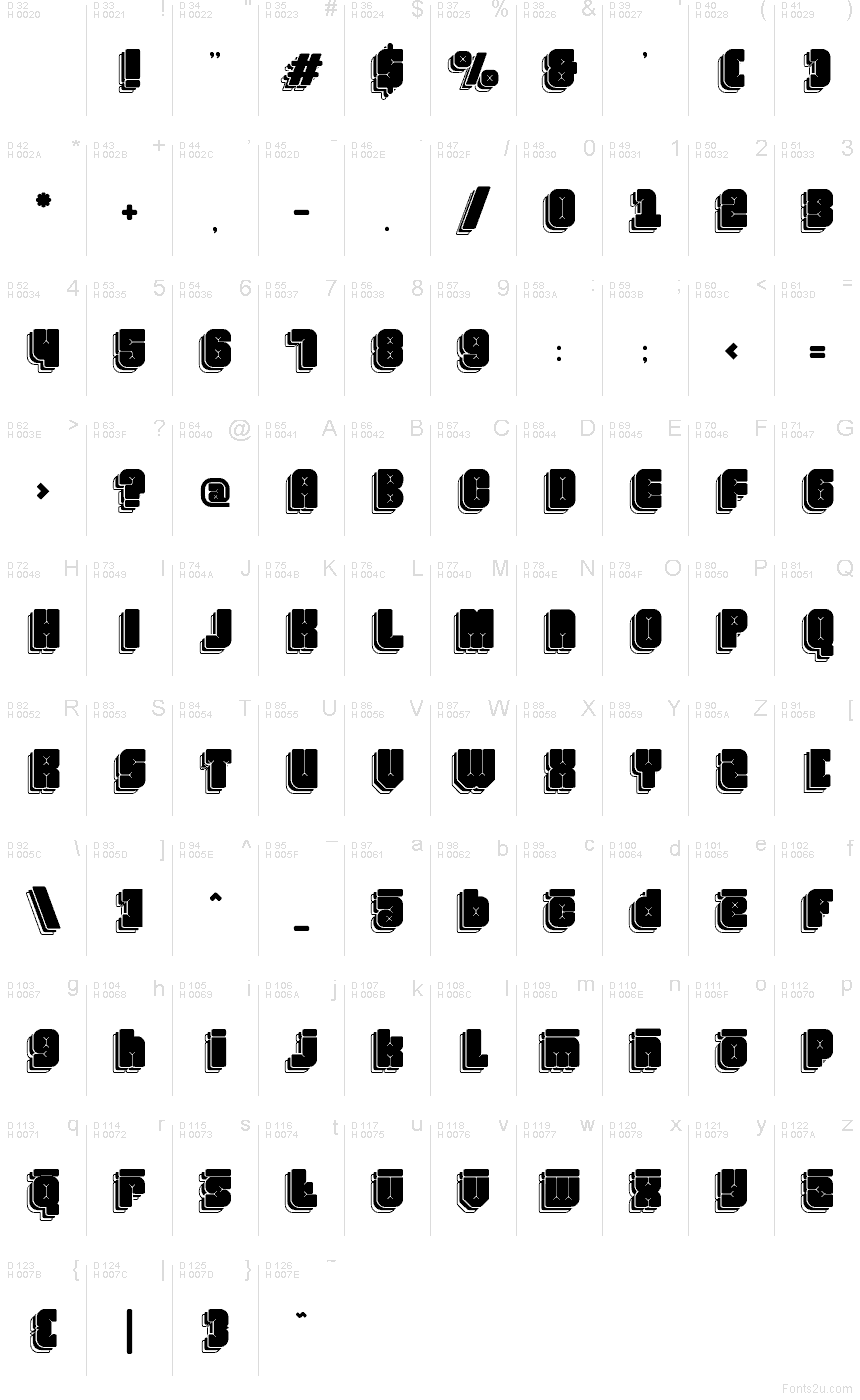
Friez Eight
Friez Eight od Putracetol Studio je groovy 3D display písmo postavené na nafouklých obdélníkových tvarech a paralelních odsazených obrysech, které každé písmeno doprovázejí jako tištěný stín. Toto opakované vrstvení dodává písmu plakátovou dynamiku, zatímco zaoblené rohy a malé vnitřní řezy zabraňují tomu, aby blokové siluety působily staticky.
Skvěle se hodí na obaly alb, párty letáky, plakáty, obaly produktů a hlavičky na sociálních sítích, kde krátký řádek textu potřebuje výrazný retro vzhled bez nutnosti dalších ilustrací. Efekt vrstveného obrysu odvádí většinu vizuální práce sám o sobě, takže Friez Eight dokáže ukotvit název, logotyp nebo grafiku na merchandise s minimem dalších prvků.